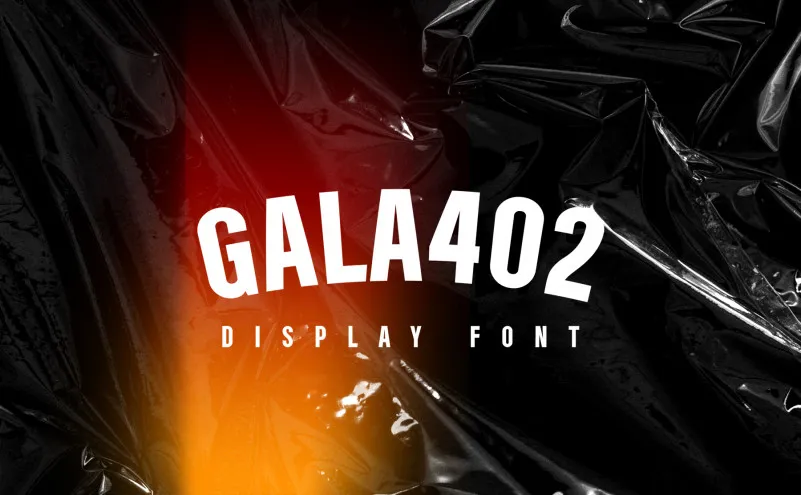
A Galáxia 402 Font é uma elegante fonte gira-fontes que foi criada pela freeject.net Design. Esta fonte adere a uma arquitetura futurista e moderna, oferecendo um estilo luxuoso e refinado. Ela não apenas traz à vida as letras, números e símbolos necessários, mas também proporciona o aspecto sofisticado que você precisa para dar ao seu design aquela pitada de extravagância elegante. Seja em logotipos empresariais ou elementos gráficos, a Galáxia 402 Font garante um visual único e arrojado. Como parte da categoria de fontes gira-fontes, ela é uma escolha inteligente para qualquer projeto que busca aquela sensação futurista, combinando modernidade com elegância.